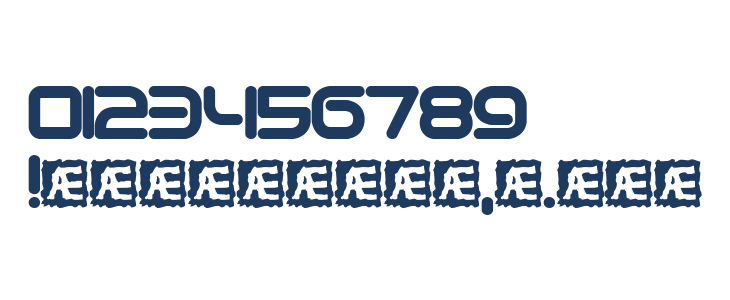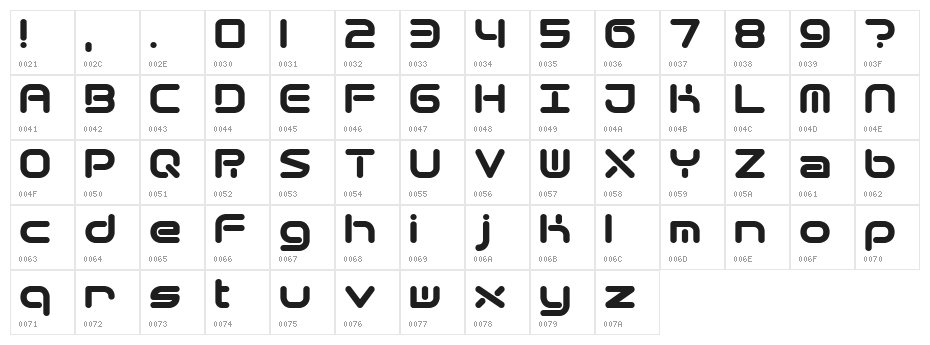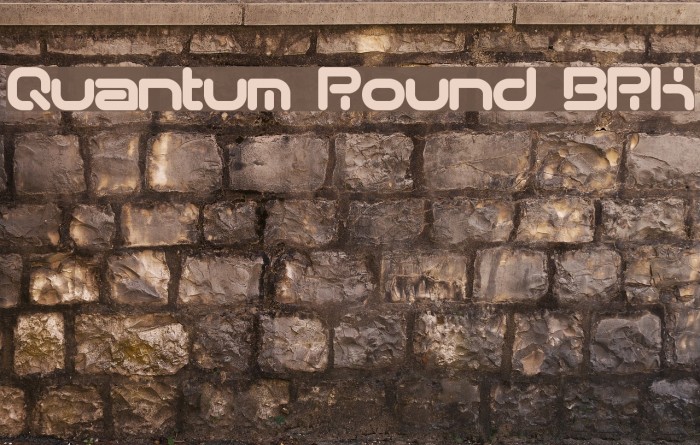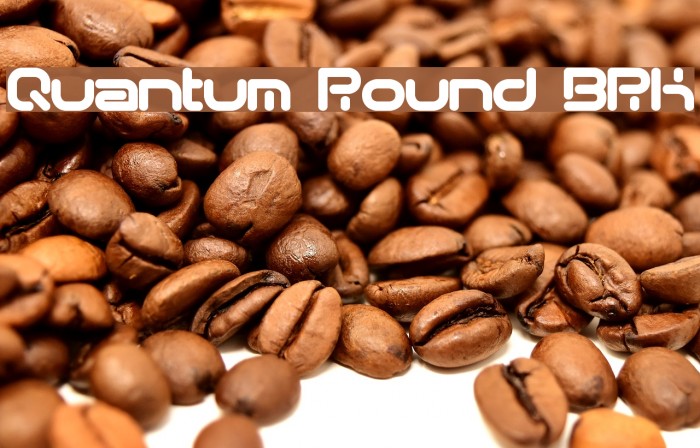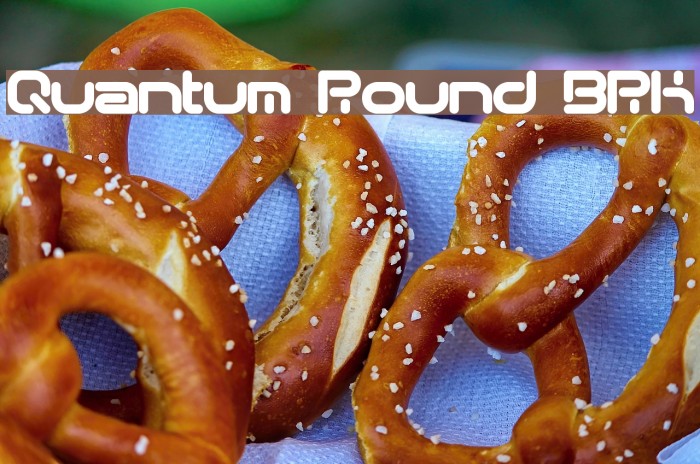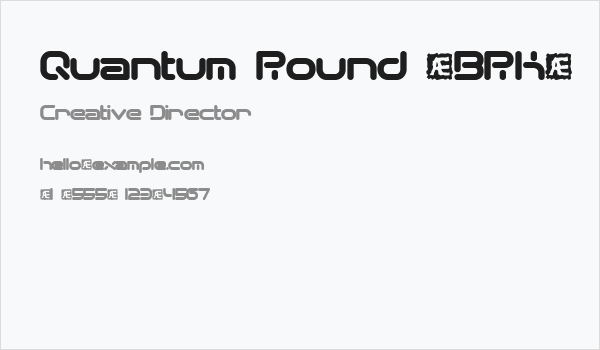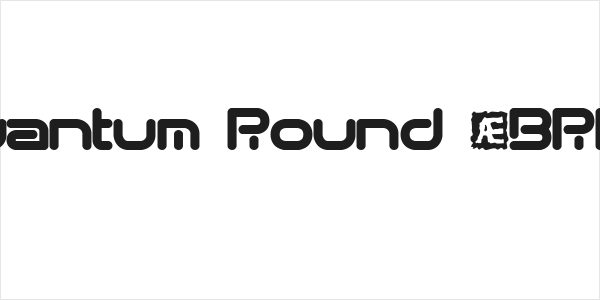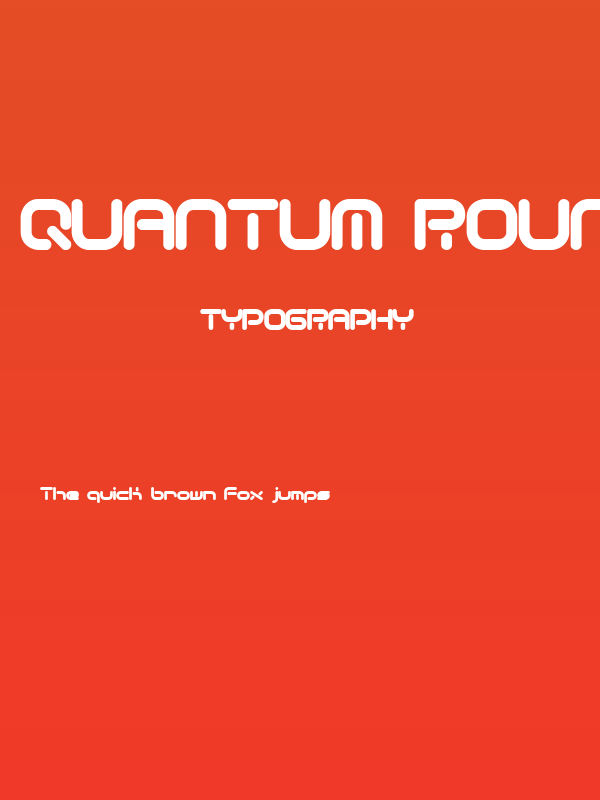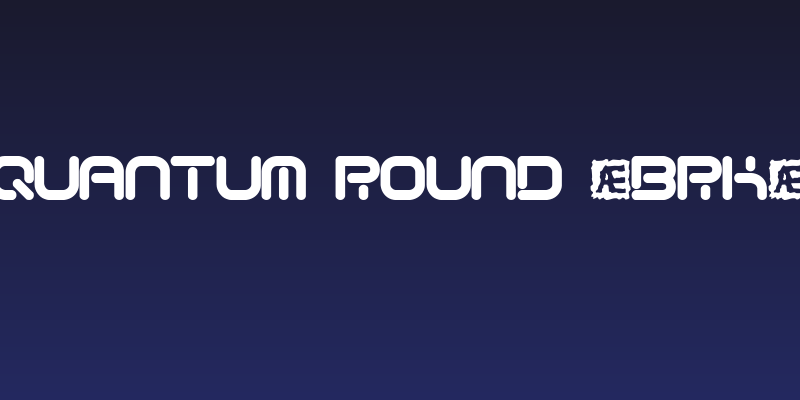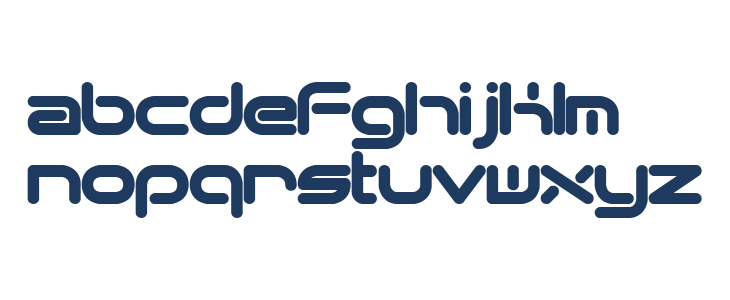
Quantum Round [BRK] Font
| Caso d'uso | Headlines, Logos, Digital Interfaces |
| Progetti proposti | Ideal for tech branding, sci-fi themed projects, modern advertising, and digital interfaces. |